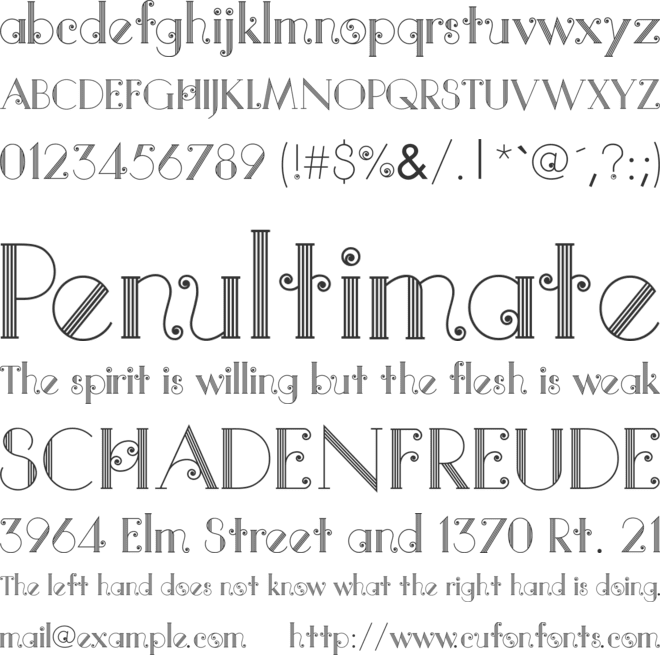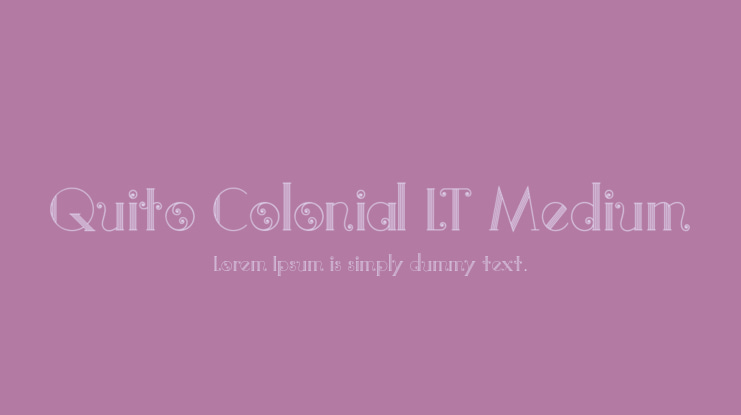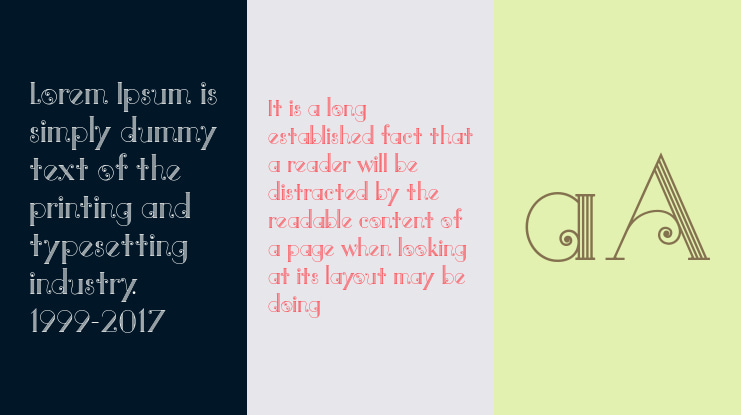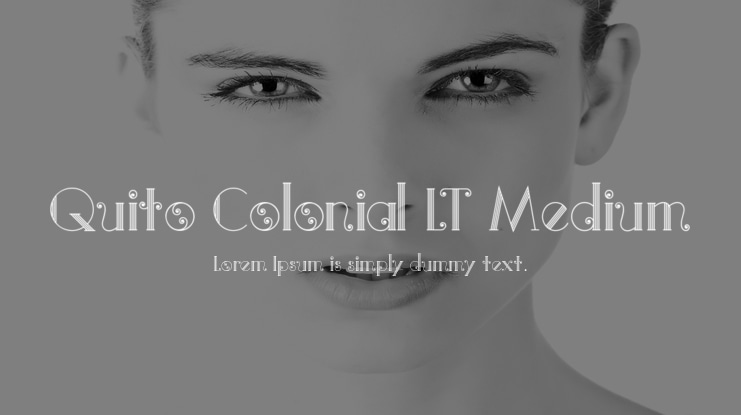
Quito Colonial LT Medium Font
David Ortega
Esta tipografia esta inspirada en el Centro Histórico de la Ciudad de Quito, Ecuador, el concepto empleado es el uso de elementos arquitectónicos que se repiten en la mayoría de construcciones, estos son las columnas de estilo neoclásico y los balcones forjados en estilo art nouveau, mezclados para representar el estilo ecléctico que caracteriza este lugar.